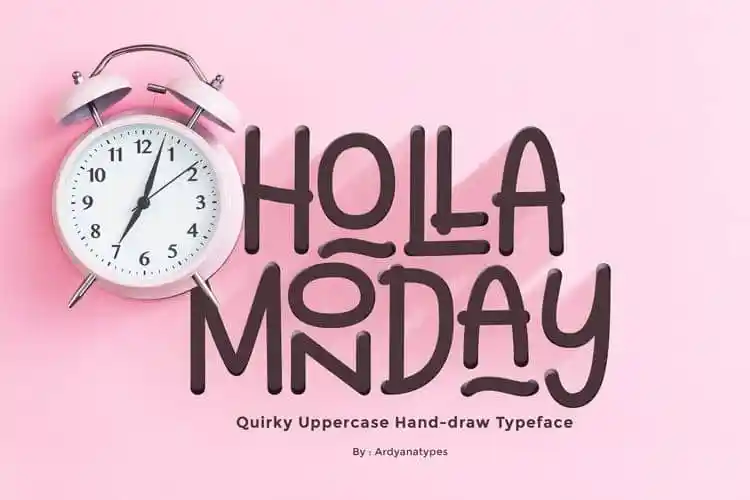
Holla Monday Display Font – Fonte Grátis
Holla Monday Display Font
A ‘Holla Monday Display Font’ é uma bela tipografia escrita à mão com ligaturas e alternativas de letras maiúsculas. Ela foi projetada pela Ardyanatypes e compartilhada pelo 99designs, fornecendo um toque amigável a cada caractere que pode ser convertido automaticamente em um selo. Isso lhe dá uma aparência leve e encorajadora, tornando-a perfeitamente acessível para uso em diversos projetos de design, como as folhas de postagem, roupas, logomarcas, citações, capas de livros, cartões de negócios, designs de produtos e muito mais. Com seu próprio charme, a ‘Holla Monday Display Font’ não só reforça o impacto visual em seus projetos design, mas também adiciona um toque divertido e inovador ao conjunto do trabalho.